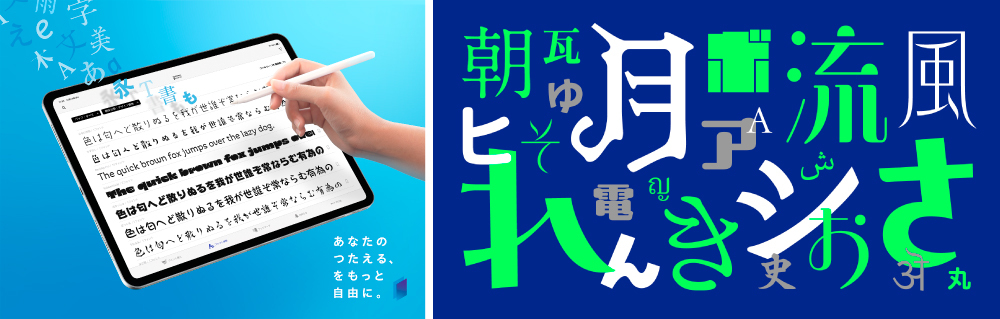
フォント提供アプリ「MORISAWA PASSPORT for iPad」Ver1.7.0をリリース 人気書体「A1明朝」の新ウエイトを含む2023年新書体を追加!
モリサワは、モリサワフォントがiPadで使えるフォント提供アプリ「MORISAWA PASSPORT for iPad」のVer1.7.0 をリリースしたことを2023年10月18日(水)に発表した。
今回のバージョンアップでは、2023年新書体に加えて定番書体のAP版など新たな書体がラインナップされる。
2023年新書体では、墨だまりの味わいを特徴とする人気書体「A1明朝(AP版)」の3ウエイトの提供、直線で力強いイメージの「ボルクロイド」、ミステリアスな「月下香(げっかこう)」、幾何学的な骨格で丸みのあるエレメントの「アルデオ」、可愛らしさと真面目さのバランスが絶妙な「つぶてん」など広告や動画テロップ、印象的な見出しに映えるデザイン書体が登場。
そして今シーズンのリリースによって、2023年現在のモリサワライブラリーにおけるA-OTF書体はAP版書体化、A-OTFかな書体は全て総合書体化され、iPadを使ったデザイン環境がより豊かになる。